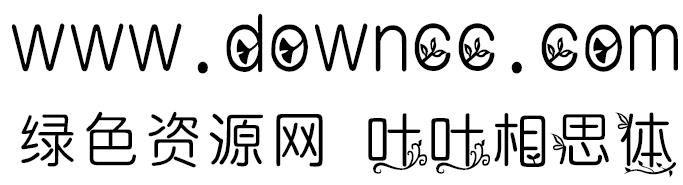
羿創(chuàng)葉葉相思體原版
漢儀葉葉相思體字體的每一個(gè)字體都仿佛擁有一種魔力,讓你能夠感受到脈脈相似的視覺(jué)享受,通過(guò)直接安裝就能夠使用,每一個(gè)字體都像是從樹(shù)葉上落下一樣,很好看!
葉葉相思體原版字體介紹
羿創(chuàng)葉葉相思體官方介紹
是一款生動(dòng)活潑的中文字體,該字體有葉子花藤環(huán)繞在上面,看起來(lái)非常的唯美,這款字體適用于設(shè)計(jì)方面的應(yīng)用!